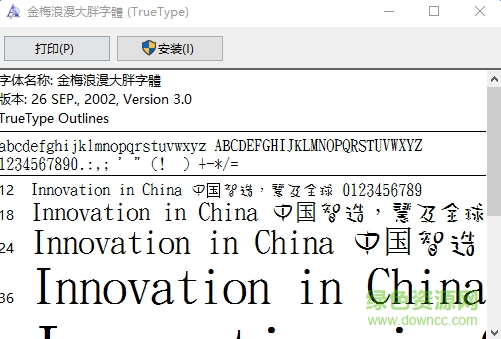
金梅浪漫大胖字體是一款具有藝術(shù)風(fēng)格的字體,這款字體可不像普通字體那樣規(guī)規(guī)矩矩的,它是有自己個性的,虛虛實實就是它最大的特點,喜歡這款字體的朋友就來綠色資源網(wǎng)下載吧。
這款字體說實話實用性還是不錯的,比如我自己就會把它用在p圖上面,這樣就會顯得圖片很美觀,大家也可以試一試哦!